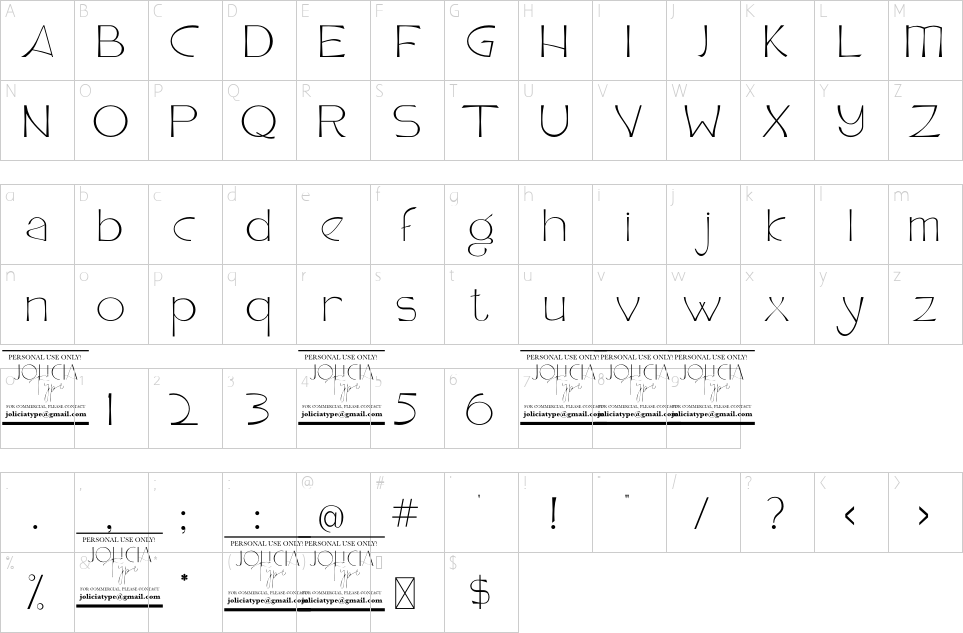
Algeron Font – Download Grátis
A Algeron Font é uma opção elegante e versátil para designers gráficos do Brasil e do mundo. Desenhada pelo designer Laire Banyu Sandi Pawenang, esta fonte é perfeita para quem procura um estilo moderno e sofisticado para seus projetos. Com uma aparência harmônica e uma paleta de cores sutil, a Algeron se destaca para criar materiais que expressam elegância e criatividade. Embora não tenha sido criada especificamente para o mercado brasileiro, a Algeron é um grande favorito entre designers por sua facilidade de uso e sua variedade de usos, desde gráficos de marketing até design editorial. Com o download gratuito da Algeron Font para Windows e Mac, você pode experimentar seu poder e estilo. Atualmente, mais de 799 pessoas já utilizaram esta fonte para adicionar um toque único aos seus projetos.